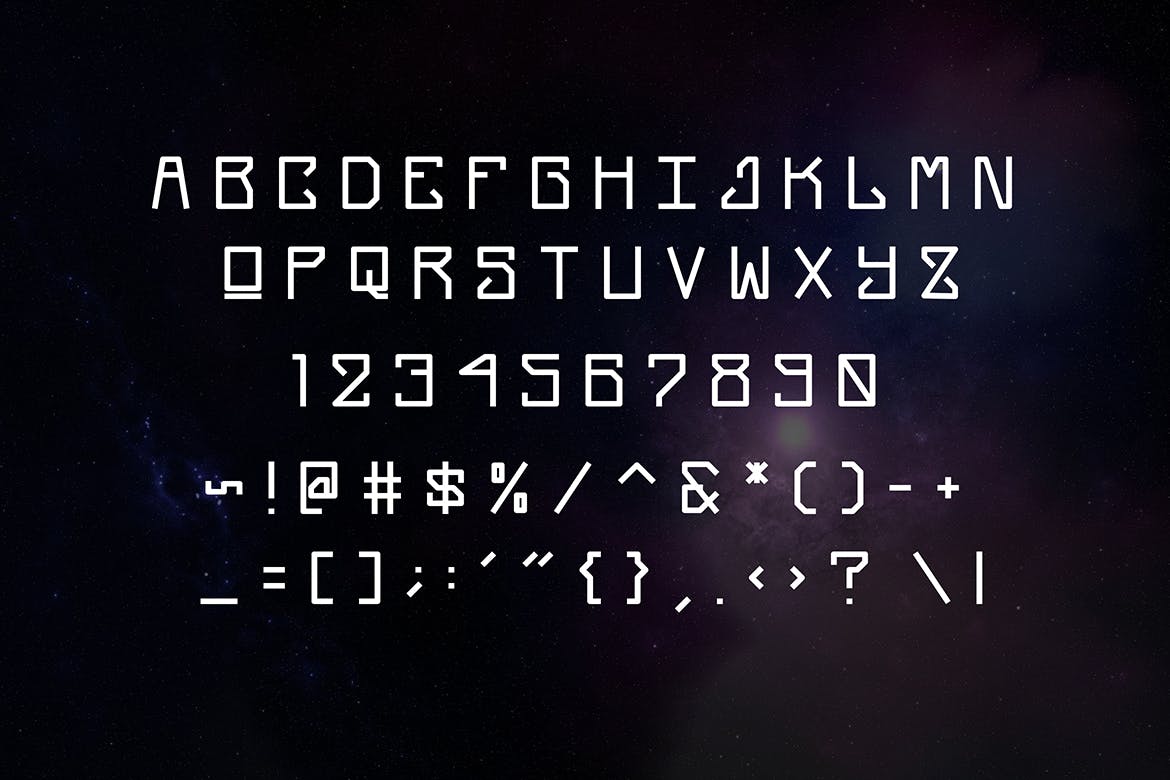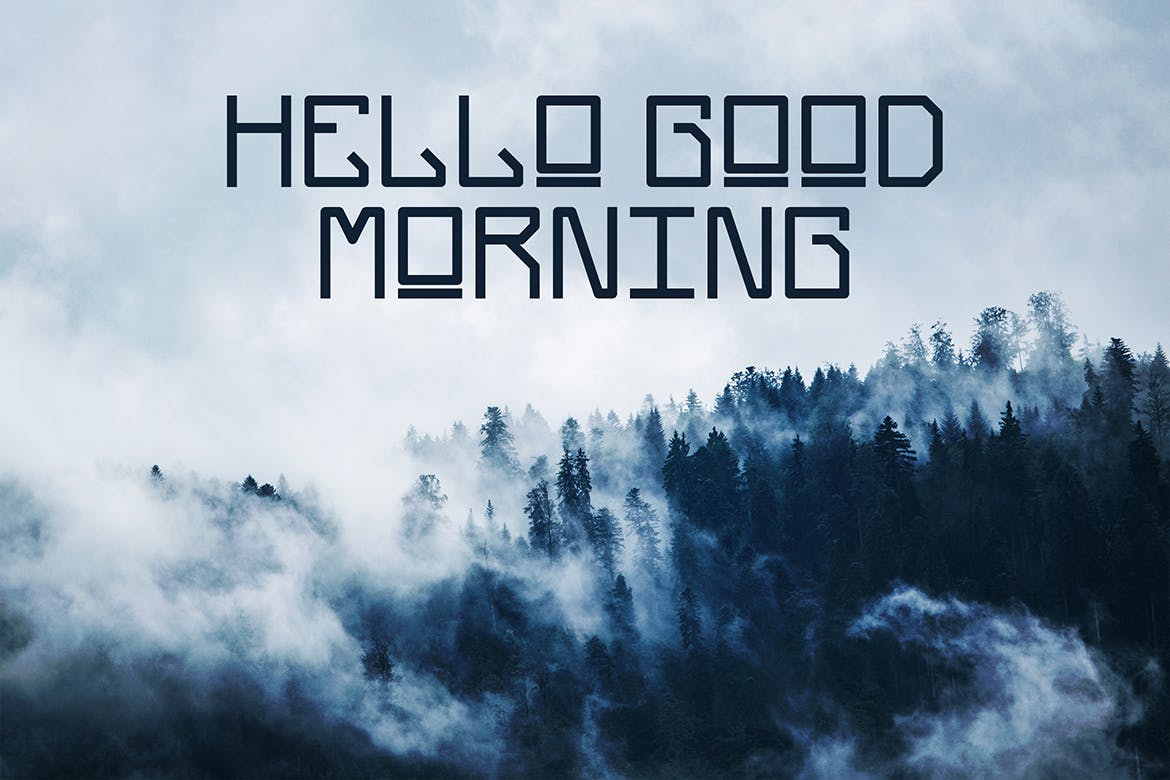
فونت لیویا (Livia) یک فونت مدرن است که با طراحی خاص و منحصر به فرد برای نیازهای شما ایجاد شده است. این فونت خنک شامل حروف بزرگ، حروف کوچک، اعداد و نمادها میباشد. فونت بسیار قوی و تیز لیویا برای عناوین، تایپوگرافی، پوسترها، مجلات، بروشورها، بستهبندی، وبسایتها و بسیاری دیگر از نیازهای طراحی شما ایدهآل است و طراحیهای شما را جذابتر میکند.